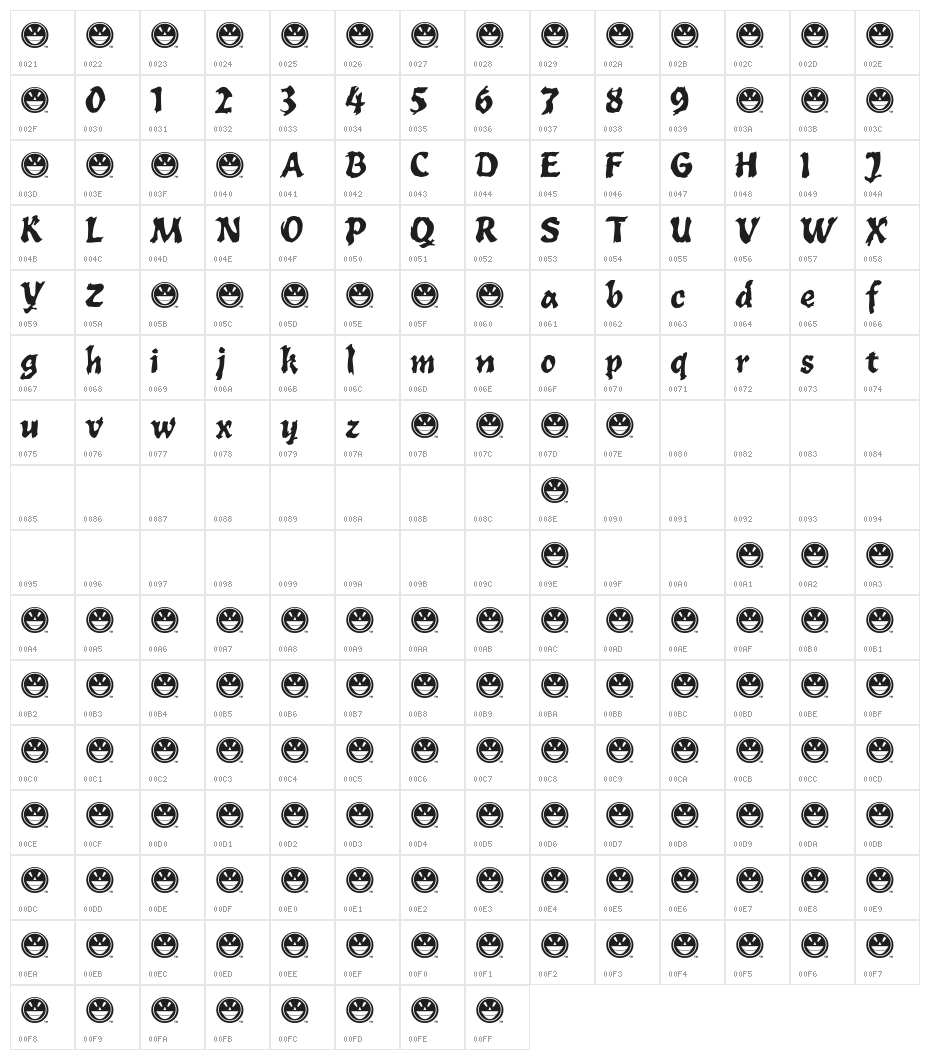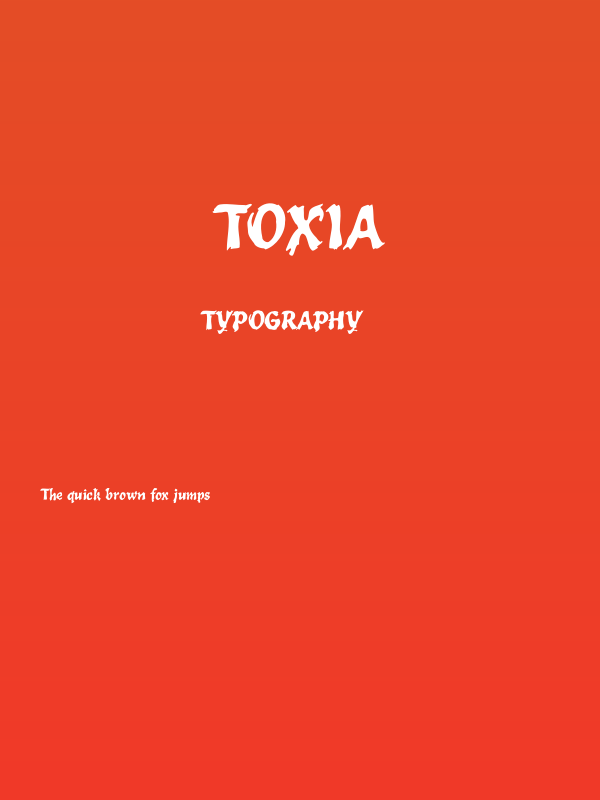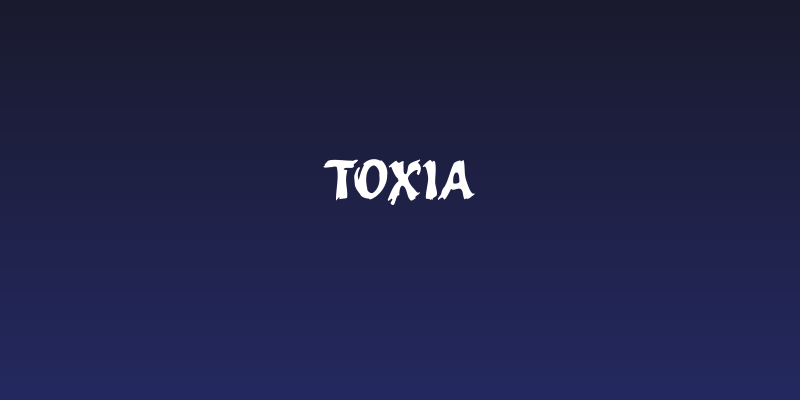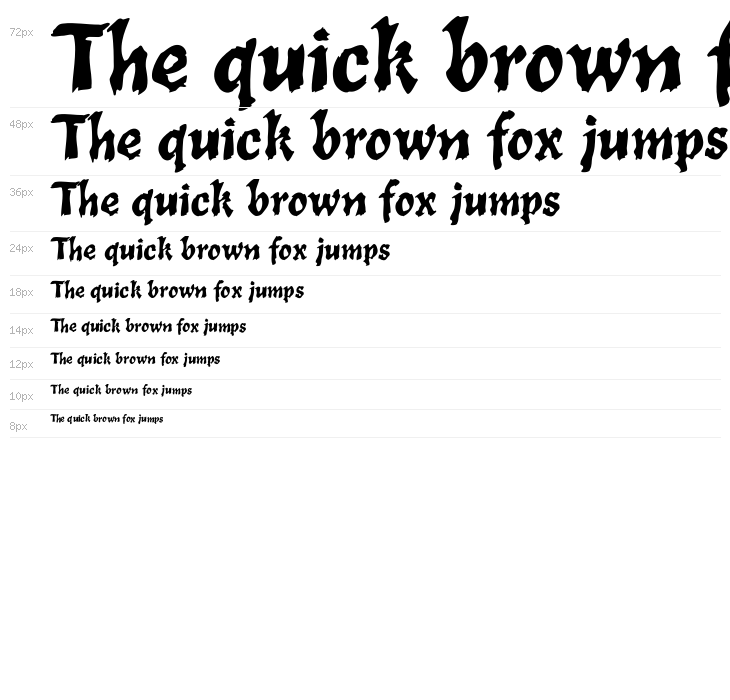
TOXIA Font
✎ Gothic
| Categorie | Gothic |
| Stile generale | Modern Gothic |
| Progetti proposti | Ideal for album covers, posters, branding for edgy or alternative products, and any design requiring a bold, dramatic statement. |